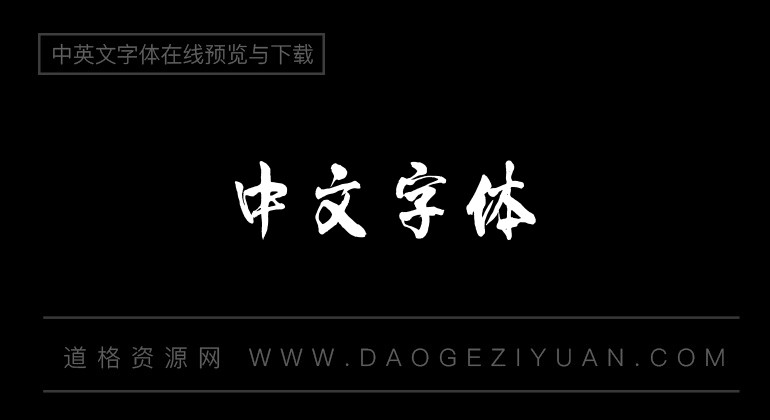
李旭科毛笔行书
李旭科毛笔行书是一种经典的中国书法字体,它源自五代时期的魏晋书法家李旭的书法作品。李旭科毛笔行书以细腻的笔画和清新的线条为特征,极具视觉冲击力。它的笔画圆润柔和,线条细腻清晰,笔划结构规整,笔法柔美温和,极具艺术魅力。它的形式简洁大方,极具表现力,可以在抒情性的文字中表达出精致的艺术效果。
李旭科毛笔行书是一款非常不错的手写艺术字体,具有很好的视觉感,适合于文化类的宣传设计、商业类品牌的广告和产品包装设计以及个性化文字排版等较多场景。